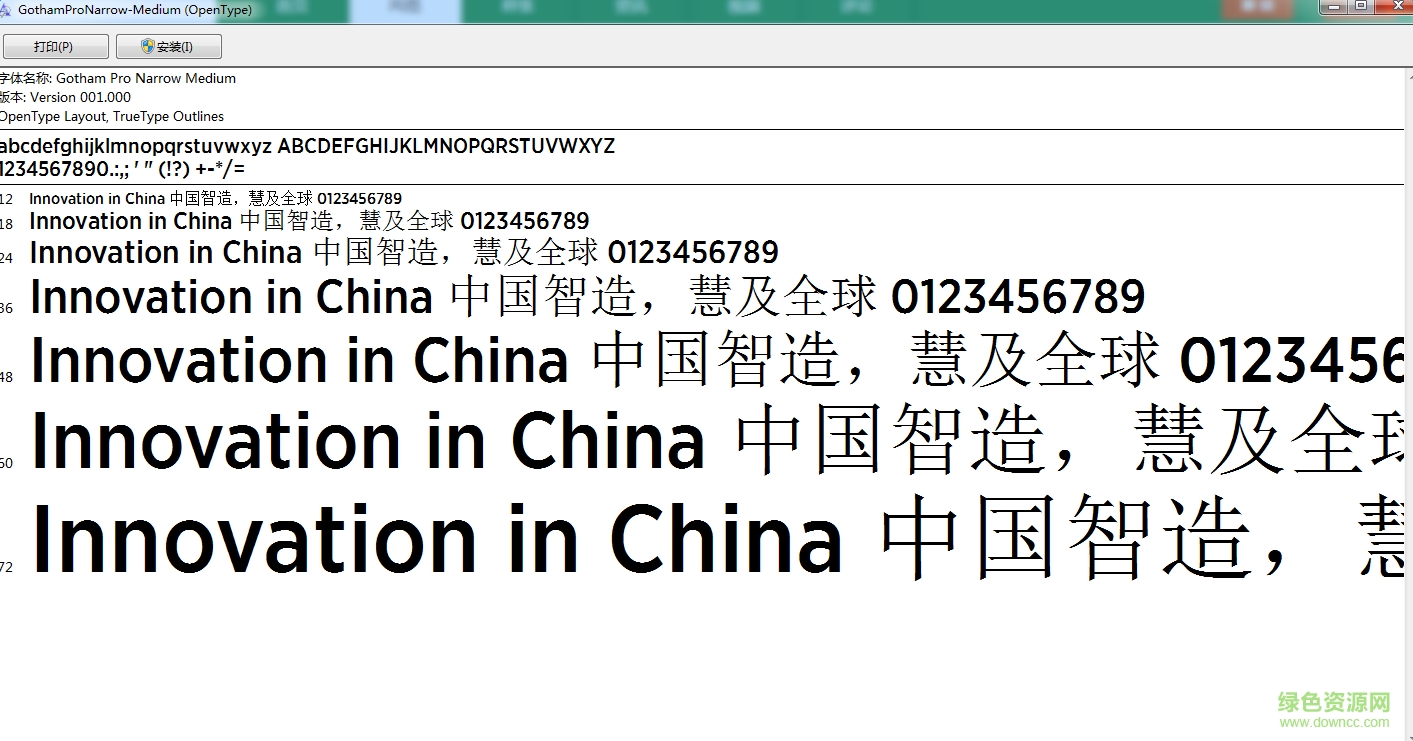
gothamnarrowbook字體
gotham narrow字體是一款經(jīng)典的英文字體,字體風(fēng)格較簡(jiǎn)約,字形精致優(yōu)雅,沒(méi)有多余的裝飾性元素,適合于產(chǎn)品包裝以及廣告宣傳領(lǐng)域,需要這款字體的朋友快來(lái)綠色資源網(wǎng)下載吧!